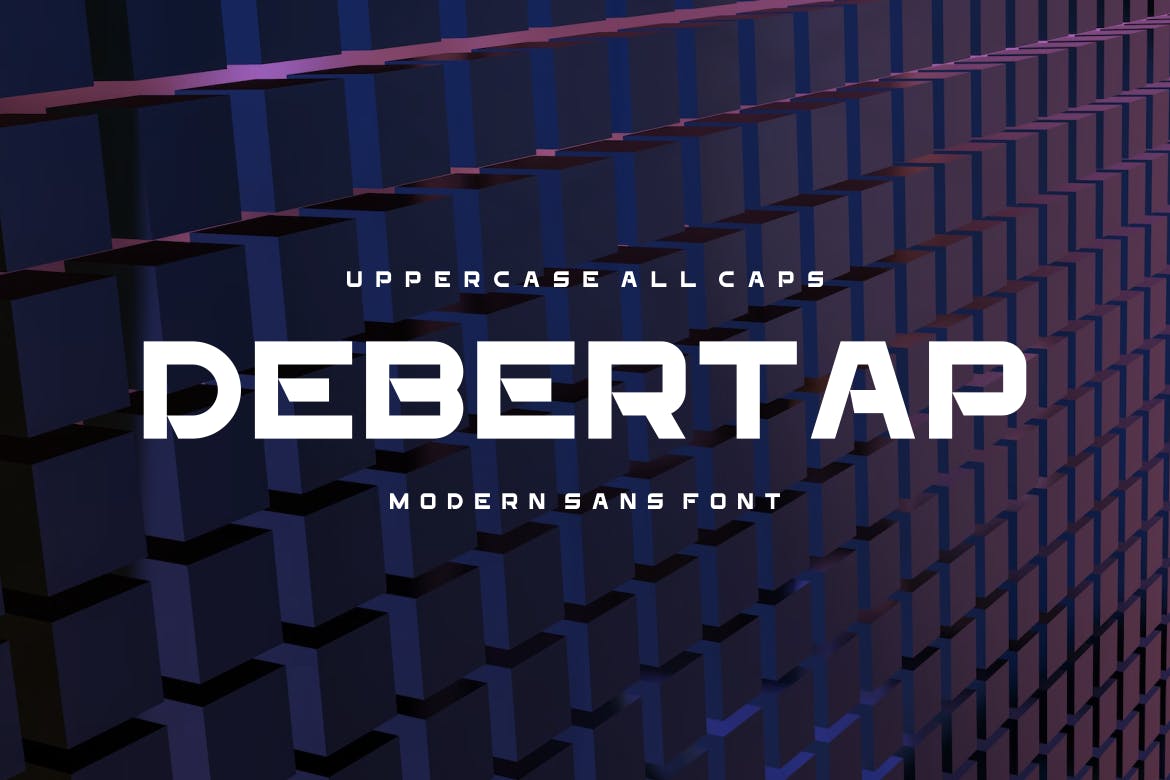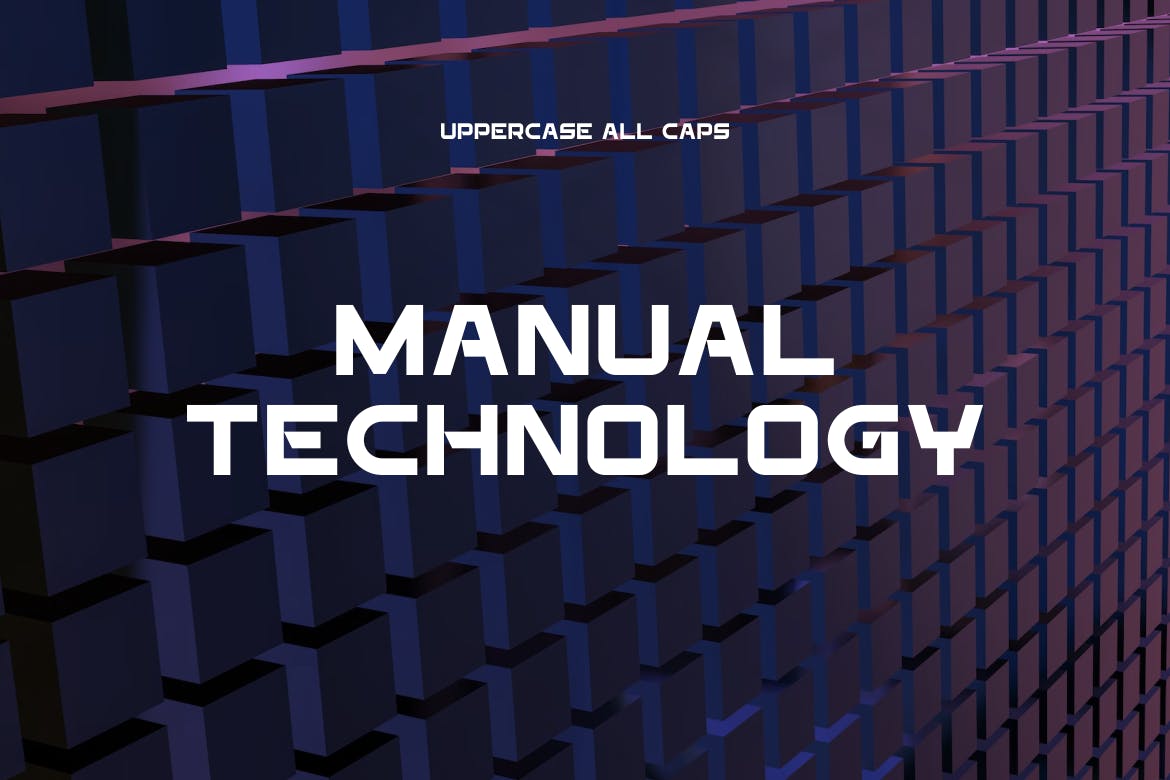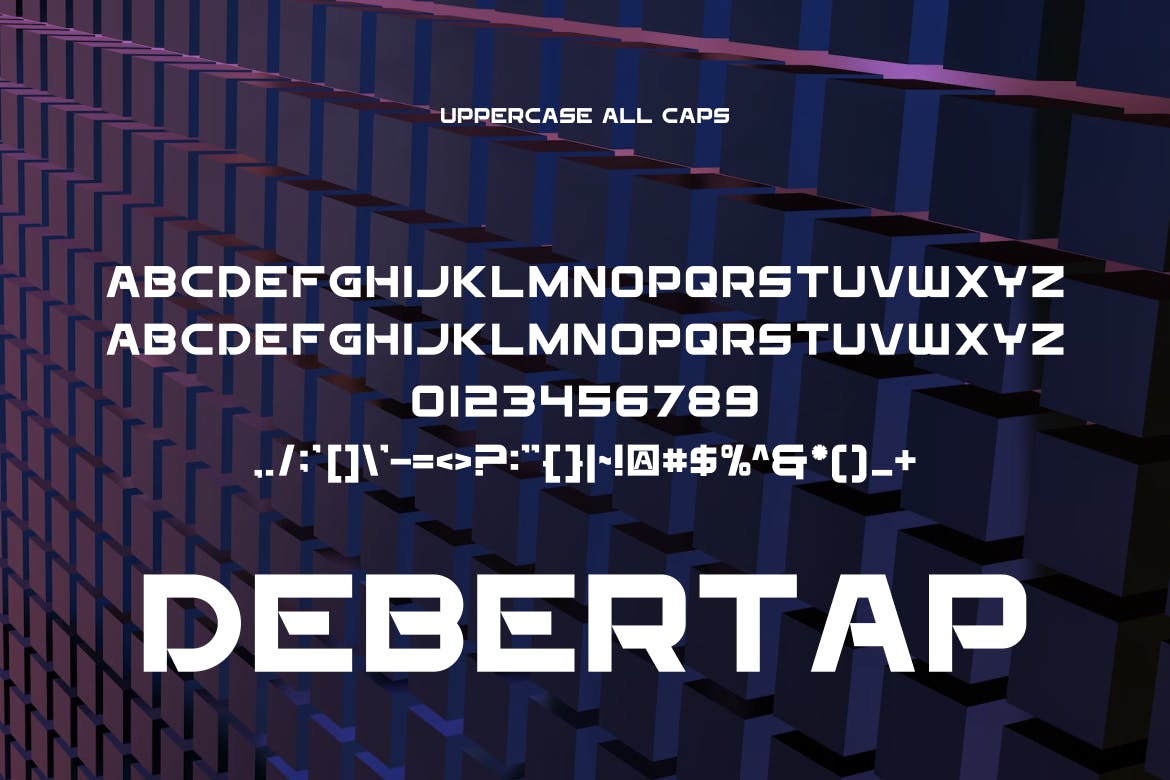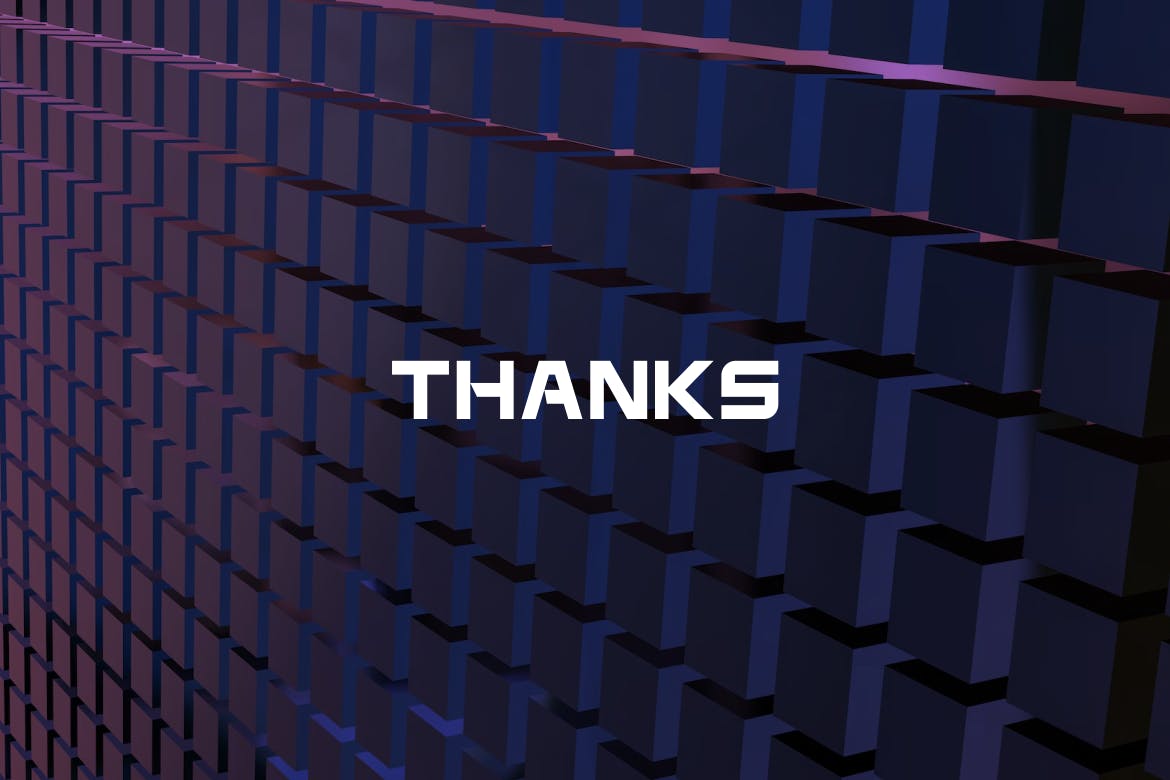
معرفی محصول جدید ما: Debertap - فونت مدرن.
Debertap - فونت مدرن یک فونت نمایشی جسور و اصیل است. این فونت برای هر پروژه برندینگ مانند لوگو مناسب است و در طیف وسیعی از زمینهها برجسته به نظر میرسد.